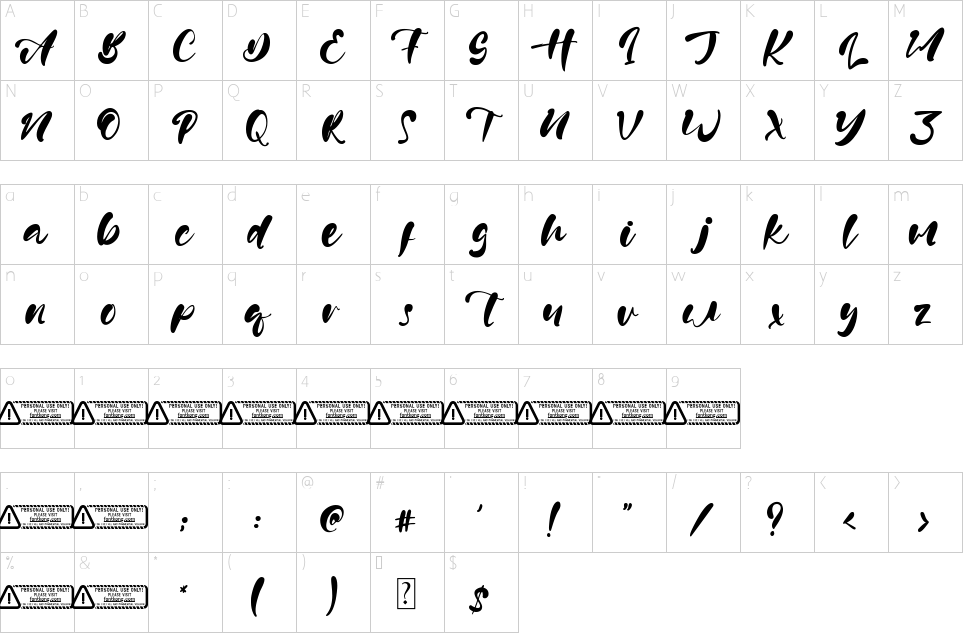
A ‘Glenn Harry Font’ é uma opção elegante para designers que buscam um visual moderno para seus projetos digitais. Desenhada por ninguém menos do que a Font Kong, essa fonte ganhou destaque entre usuários de sistemas Windows e Mac graças à sua simplicidade e legibilidade. Com seu design minimalista, a ‘Glenn Harry Font’ é perfeita para criações de sites, logotipos e texturas variadas. Com um download acumulado em 1.204 vezes, mostra que essa fonte está ganhando popularidade como uma opção confiável de gráficos gratuitos. Seja para projetos pessoais ou profissionais, a ‘Glenn Harry Font’ oferece uma ótima alternativa para aqueles procurando por uma opção livre e elegante para suas criações digitais.